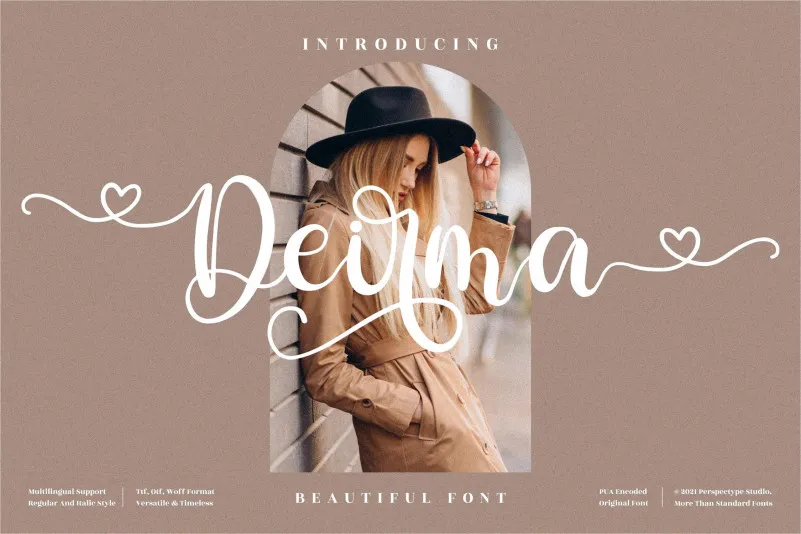
A ‘Deirma Font’ é uma elegante tipografia de letra cursiva que se destaca por suas formas delicadas e dançantes ao redor do nível base. Composta para aqueles que valorizam um toque romântico e suave nas criações digitais, esta fonte adicionará um brilho sofisticado a qualquer projeto visual de design. A característica mais notável da ‘Deirma Font’ é sua PUA encoded, uma tecnologia que permite a navegação fácil pelos inúmeros caracteres e ligaturas únicas disponíveis. Esta qualidade torna o processo de criar designs incrivelmente intuitivo e versátil. Seja para um projeto pessoal ou profissional, esta fonte oferece uma escolha sofisticada que não apenas destaca seu trabalho mas também adiciona profundamente à sua personalidade criativa. Não se limite a simples estilos convencionais – a ‘Deirma Font’ é o catalisador perfeito para projetos de design inovadores e memoráveis.